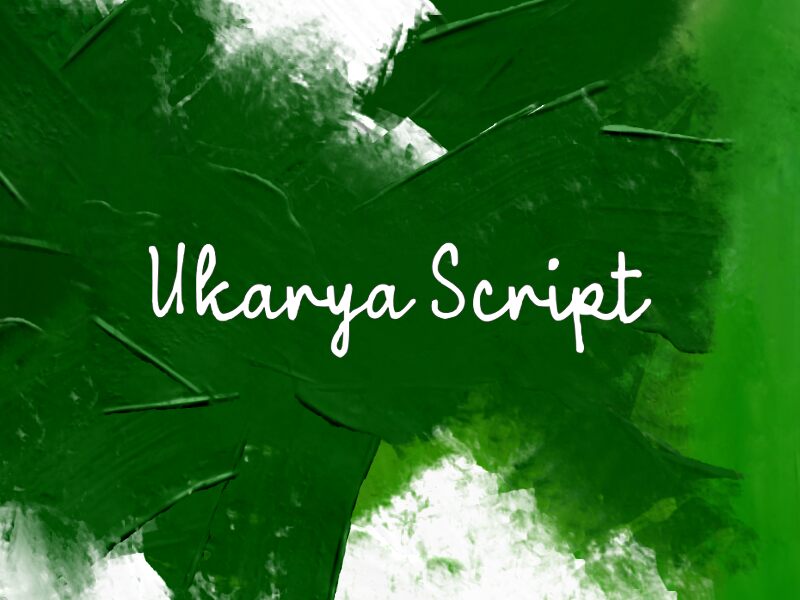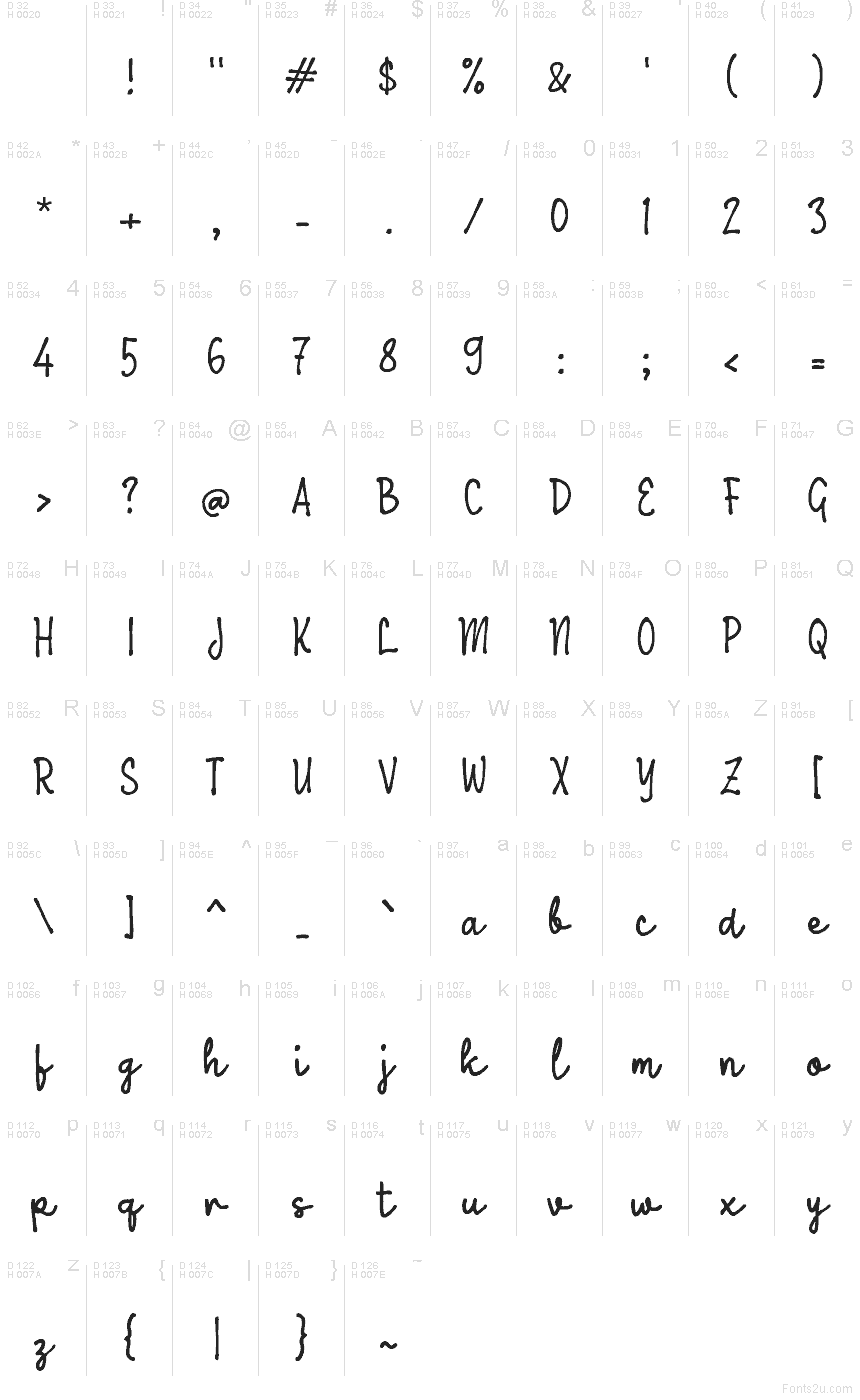
Ukarya Script
Ukarya Script от Wep — это бесплатный рукописный кистевой шрифт с легким, современным характером, напоминающим автограф. Буквы движутся в быстрых, уверенных изгибах с легкой «небрежностью» печатного края. Длинный, уходящий вниз хвост буквы «y» и естественные соединения придают шрифту личный, неформальный оттенок.
Он органично впишется в брендинг, меню кафе, упаковку, посты в соцсетях и заголовки плакатов, где требуется бесплатный шрифт с «человеческим» лицом. Используйте его для коротких заголовков, обложек, эскизов логотипов или именных знаков, особенно если вам нужно создать ощущение, будто надпись была сделана одним непринужденным движением.